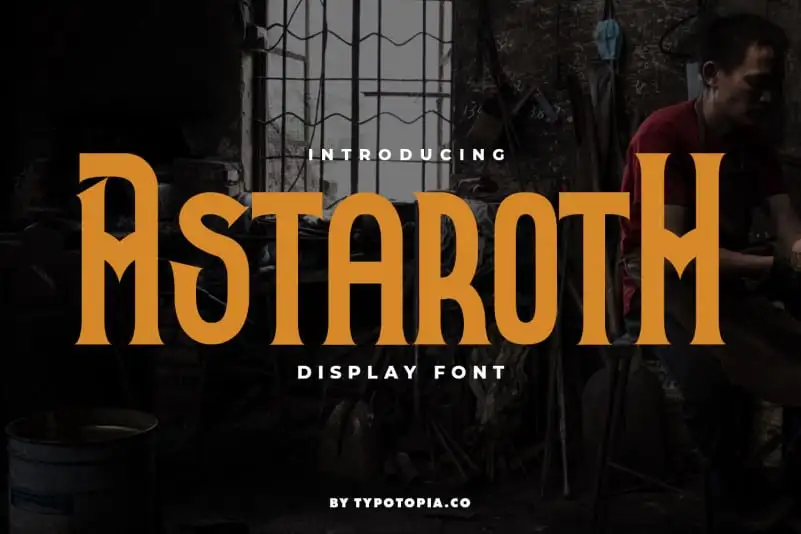
Astaroth Display Font – Download Grátis
Astaroth Display Font é uma maravilhosa escolha para designers que buscam adicionar estilo a sua próxima criação visual. Desenvolvida pelo designer typotopia, esta fonte de exibição está repleta do charme vintage e moderno ao mesmo tempo. Seu design único e versátil permite aplicação em uma ampla gama de projetos, desde logomarcas e materiais publicitários até embalagens e cartões de visita. Com seu estilo semi-vintage, Astaroth Display Font traz um ar de sofisticação ao design, combinando elementos modernos com o charme nostálgico. Este tipo de fonte é perfeitamente adaptada para aplicação em diversas mídias, como estampas de roupas, embalagens de produtos e materiais promocionais. Além disso, também se destaca nas plataformas digitais, trazendo um toque diferenciado a sites e blogues. Seja você um designer gráfico profissional ou iniciante, Astaroth Display Font é uma excelente adição ao seu armário de ferramentas para criar uma variedade de projetos que capturam o coração do público e destacam sua marca. Este tipo de fonte é como um pedaço de arte digital, capaz de transformar qualquer projeto em um verdadeiro ato de magia visual.